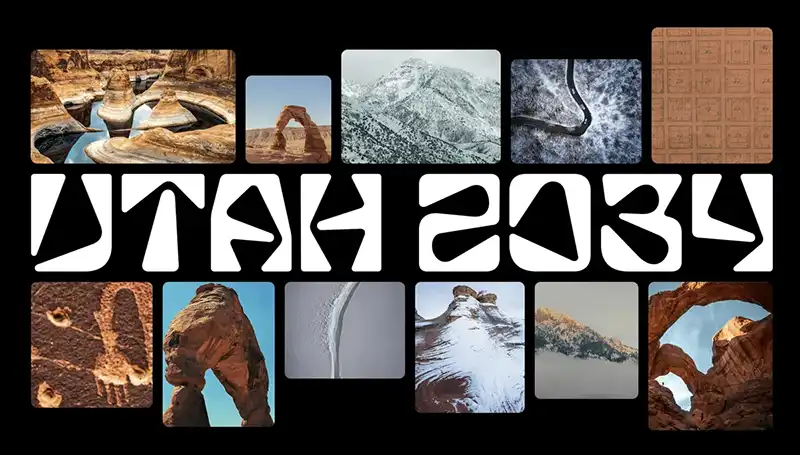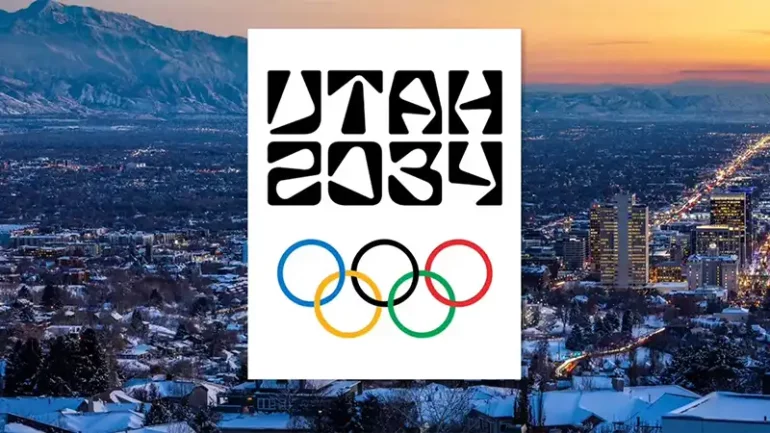
واکنش‌ها به لوگوی جدید المپیک زمستانی ۲۰۳۴؛ «شبیه فونت رستوران چینی است»
هنوز ۹ سال تا آغاز بازی‌های المپیک زمستانی ۲۰۳۴ در یوتا (ایالات متحده) باقی مانده است، اما رونمایی زودهنگام از لوگوی این رویداد به مناسبت «۳۰۰۰ روز مانده به افتتاحیه»، بحث‌های داغی را در جوامع دیزاین به راه انداخته است.
به گزارش روزرنگ، کمیته برگزاری المپیک ۲۰۳۴ یوتا اخیراً از هویت بصری جدیدی رونمایی کرد که هدف آن «اتحاد جوامع» و بازتاب جغرافیای کوهستانی و سنگ‌نگاره‌های (Petroglyphs) باستانی این ایالت عنوان شده است. این لوگو شامل یک تایپ‌فیس انتزاعی و زاویه‌دار با گوشه‌های نرم است که تلاش دارد نگاهی معاصر به المپیک داشته باشد.
«فونت رستوران چینی» یا دیزاین مدرن؟
علیرغم تلاش طراحان برای ارائه یک فرم مدرن و ساختارشکن، واکنش‌ها در فضای مجازی و پلتفرم‌هایی مانند ردیت (Reddit) چندان مثبت نبوده است. بسیاری از کاربران این تایپوگرافی را ناخوانا و بی‌ارتباط با روحیه ورزشی دانسته‌اند.
یکی از نقدهای پربازتاب در فضای دیزاین، شباهت این تایپ‌فیس به فونت‌های کلیشه‌ای «رستوران‌های چینی» یا فونت‌های آماده‌ و سایکدلیک نرم‌افزار Canva بوده است. منتقدی می‌نویسد: «هیچ ارتباطی با المان‌های جغرافیایی ادعا شده در آن نمی‌بینم.» با این حال، برخی دیگر جسارت فاصله گرفتن از لوگوهای ورزشی سنتی و خسته‌کننده را ستوده‌اند و معتقدند که این طرح دست‌کم «کسالت‌بار» نیست.
یک لوگوی موقت
نکته‌ای که شاید از شدت انتقادات بکاهد، ماهیت موقتی این لوگو است. طبق اعلام مسئولان، این نشان صرفاً یک هویت بصری انتقالی (Placeholder) است و لوگوی رسمی و نهایی المپیک زمستانی ۲۰۳۴ قرار است در سال ۲۰۲۹ رونمایی شود.
طراحی لوگوهای ورزشی همواره یکی از چالش‌برانگیزترین حوزه‌های گرافیک دیزاین بوده است و باید دید آیا مخاطبان در طول ۹ سال آینده با این فرم بصری ارتباط برقرار خواهند کرد یا خیر.